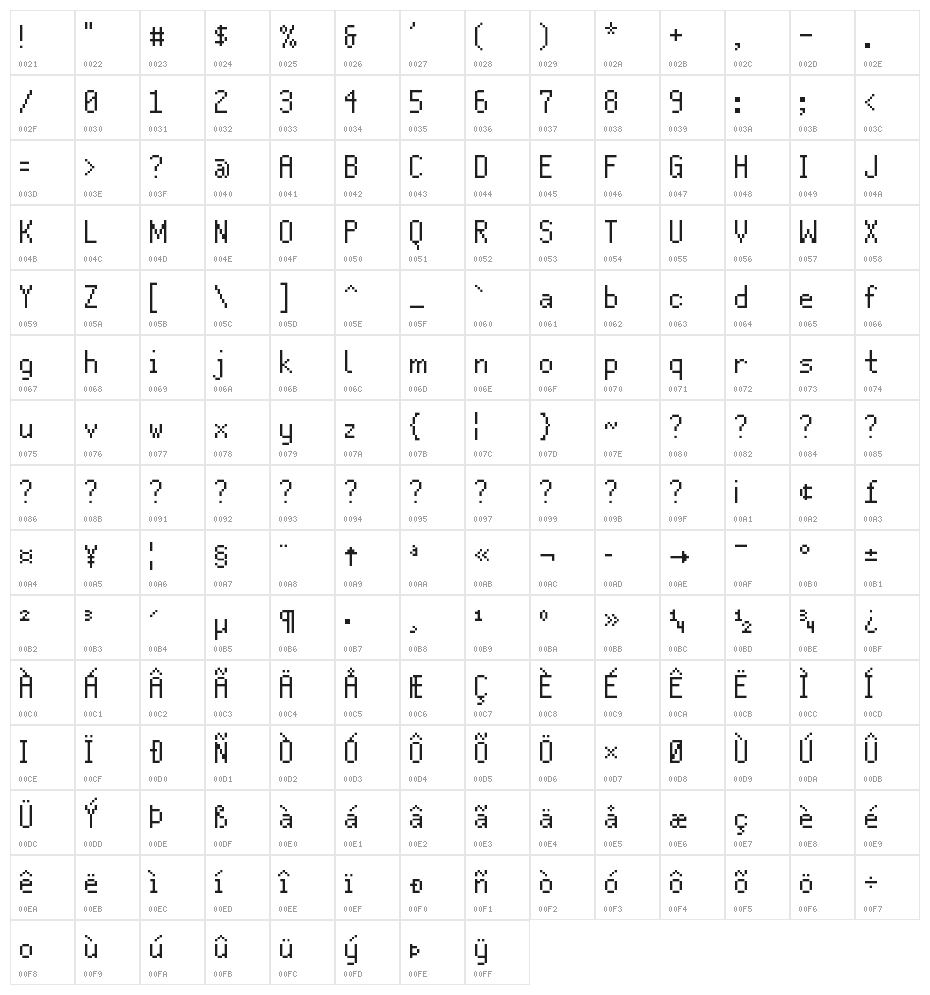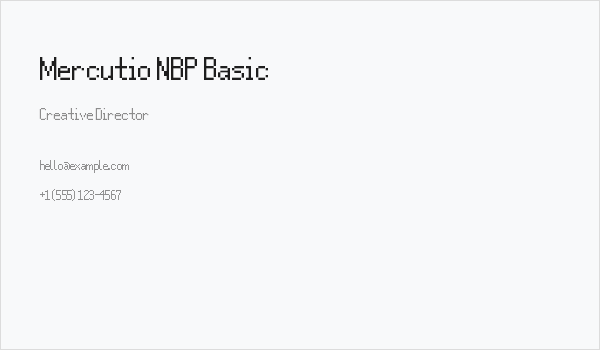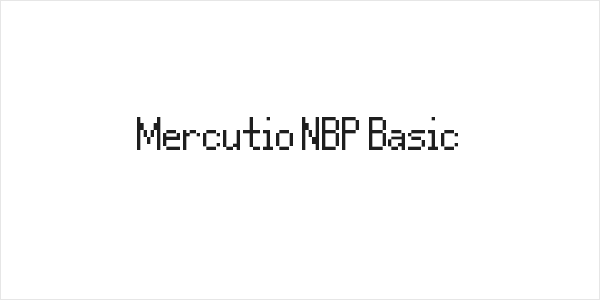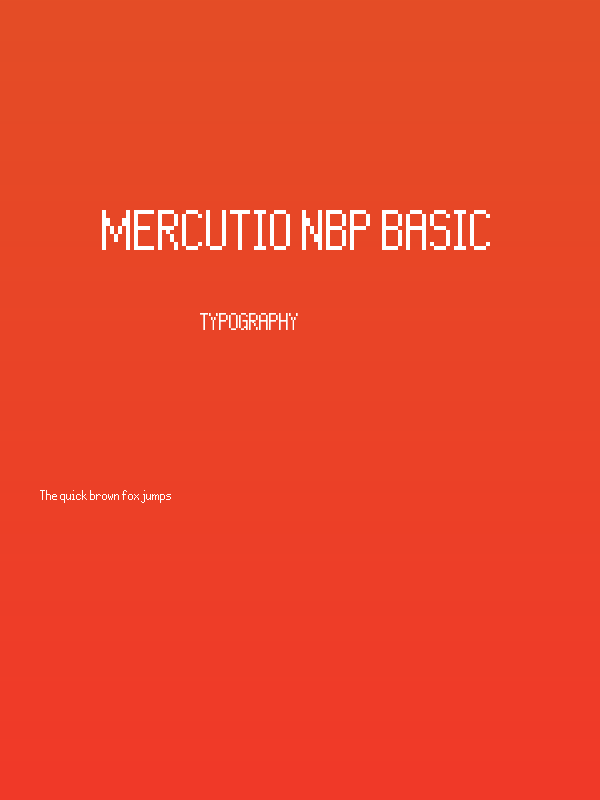
Mercutio NBP Basic Font
| Categorie | Pixel |
| Stile generale | Retro, Digital |
| Caso d'uso | Headlines, Logos, Digital displays |
| Progetti proposti | Ideal for video game design, retro-themed websites, digital art projects, and coding interfaces. |